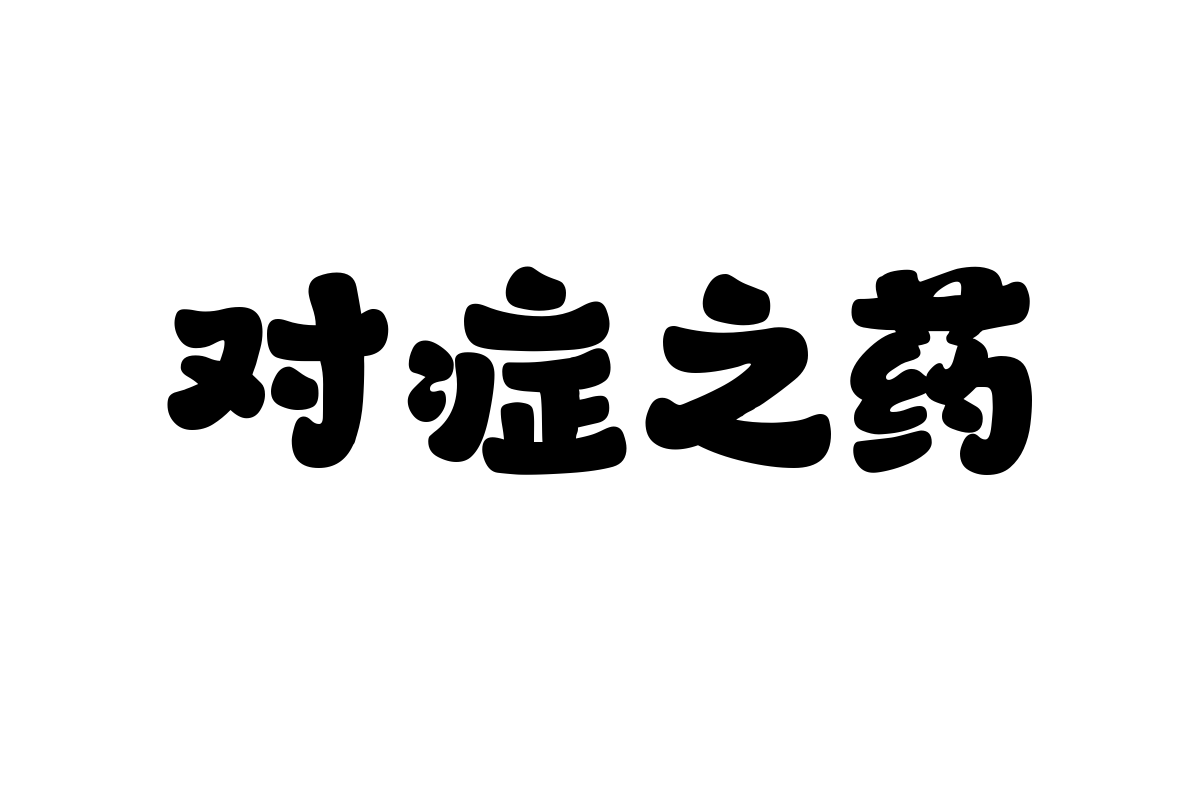
山海牛奶波波W是一款免费开源的中文字体,由台湾设计师李明川于2015年设计。这款字体以其独特的造型和流畅的线条而受到欢迎,广泛应用于网页、海报、广告等各种设计领域。
山海牛奶波波W的特点如下:
1. 字形独特:这款字体采用了独特的“波浪形”设计,使得每个字母都呈现出不同的形态,增加了视觉冲击力。
2. 风格鲜明:山海牛奶波波W的设计风格独特,给人一种清新自然的感觉,适合用于需要突出个性和创意的设计作品。
3. 可读性强:虽然字体独特,但整体布局和笔画粗细适中,使得阅读起来依然清晰易懂。
总之,山海牛奶波波W是一款具有独特造型和风格的中文字体,适合用于需要突出个性和创意的设计作品。